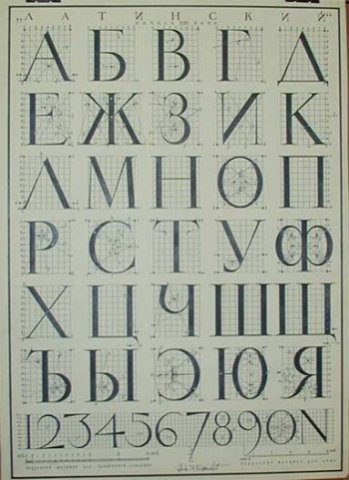
Антиквы
Их форма ведет свое происхождение от шрифта древнеримских монументальных надписей (прописные буквы) и от книжного гуманистического минускула эпохи Ренессанса (строчные буквы). Первая наборная антиква появилась в Италии и Германии во второй половине XV века. В дальнейшем форма латинской антиквы развивалась: на смену антикве старого стиля (конец XV – начало XVIII в.в.) пришла переходная антиква (начало XVIII – конец XVIII в.в.), которая сменилась антиквой нового стиля (конец XVIII – начало XIX в.в.), кроме того, в начале XIX в.появились брусковые шрифты. На основе этих исторических форм современные дизайнеры шрифтов создают новые версии антиквенных шрифтов.
Представляет собой первый этап развития антиквенных шрифтов (с конца XV по начало XVIII века). Форма знаков этого шрифта основана на дуктальном (рукописном) принципе, она характеризуется умеренной контрастностью, скруглением засечек в местах примыкания к основному штриху и наклоном осей овальных элементов.
Эти шрифты делятся на несколько подгрупп в соответствии с временем и местом своего появления: это венецианская антиква (конец XV века), итальянско-французская антиква (XVI век), голландская антиква (XVII век), английская антиква (начало XVIII века) и современные версии антиквы старого стиля.
Венецианская антиква
Ранняя антиква (конец XV века), включающая элементы готики. Этот шрифт иногда выделяют в отдельную группу классификации Humanist (так назывемая Гуманистическая антиква). Форма знаков основана на дуктальном принципе.
Шрифты характеризуются умеренной контрастностью, мощными короткими засечками, хорошо выраженным наклоном осей овалов и размашистыми пропорциями. Круглые элементы имеют каллиграфические изломы, капли угловатые. Среди исходных венецианских шрифтов этого периода нет курсивов, они были изобретены позднее.
Итальянско-французская антиква (Гаральды)
Представляет собой дальнейшее развитие венецианской антиквы в XVI веке. В этот период форма знаков французской антиквы все еще основывается на дуктальном принципе, однако она постепенно меняется под воздействием типографской практики и эстетических теорий того времени. Шрифты характеризуются небольшим контрастом, пропорциями золотого сечения, разноширинностью знаков, плавным присоединением засечек и наклонными осями овалов. Засечки становятся более длинными и острыми, а верхние выносные элементы, как правило, заметно выше прописных знаков. В этот период в качестве альтернативного текстового шрифта впервые применяется строчной курсив с небольшим наклоном.
Барочная антиква
Барочная антиква уже почти не напоминает гуманистический мину-
скул. Она заметно контрастнее венецианской и итало-французской, фор-
ма капель и других элементов в ней ближе к геометрически правильной,
кальная ось овала буквы о и наклонные — с и е.
Однако открытой формы знаков и общего характера набора достаточно,
чтобы барочная антиква оставалась динамической.
Разница в форме разновидностей барочной антиквы — голландской
и английской — невелика.
1. Голландская антиква
Представляет собой дальнейшее развитие форм французской антиквы в XVII веке.
Эти шрифты выполнены более качественно, для них характерно постепенное нарастание особенностей, свойственных глиптальным шрифтам (увеличение контраста и насыщенности, более острые засечки, оси овалов более вертикальны) при сохранении традиционной формы антиквы старого стиля. Шрифты довольно узкие, а очко строчных имеет более округлую форму. Рост прописных приближается к высоте верхних выносных элементов. В курсиве наклон у прописных меньше, чем у строчных. Строчные курсивные знаки имеют разный наклон. Угол наклона строчных знаков в курсиве больше, чем во французской антикве.
2. Английская антиква
Шрифты первой половины XVIII века, созданные в Англии как улучшение голландской антиквы. Детали почти целиком определяются глиптальными принципами, однако форма знаков в значительной степени традиционно повторяет более раннюю антикву старого стиля. Знаки этих шрифтов более контрастны и насыщены, засечки тоньше и острее, а оси овалов почти вертикальны. Пропорции знаков гораздо шире, чем в голландской антикве, знаки разноширинные.
Современные версии шрифтов на основе антиквы старого стиля, не имеющие конкретных прототипов и отличающиеся по форме.
Переходная
Шрифты начала и середины XVIII века, сочетающие черты шрифтов старого стиля, характерные для письма широким пером, и элементы шрифтов нового стиля, форма которых связана с особенностями процесса гравировки по металлу.
Эта форма переходной антиквы почти не связана с антиквой старого стиля. Она основана на глиптальных принципах, связанных с рисованием и гравировкой металлических пуансонов. Знаки более контрастны, а соединительные штрихи и засечки тоньше, чем в антикве старого стиля. Скругления засечек в местах соединения с основными штрихами выражены слабо. Оси овалов некоторых знаков почти вертикальны, у остальных знаков они имеют незначительный наклон.
Современные вариации шрифтов на основе переходной антиквы, не имеющие конкретных прототипов и отличающиеся по форме.
Нового стиля
Эти шрифты появились в конце XVIII – начале XIX века в связи с развитием техники гравировки по металлу. Одноширинные шрифты с сильным контрастом. Засечки длинные и тонкие, оси овалов строго вертикальны. По форме засечек антиква нового стиля делится на следующие группы: классицистическую, англо-шотландскую и современные вариации шрифтов на основе антиквы нового стиля.
Классицистическая антиква
Антиква Жоффруа ТориВ XVIII в.
под влиянием стиля классицизма и техники оригинальной гравюры на меди антиква меняет свои формы — возникает новая антиква, отличающаяся от старой утонченностью форм и очень большим контрастом. В буквах этого шрифта доминирует вертикаль, наблюдается сужение пропорций и глубина пространства. Соединительные штрихи стали очень тонкими, а засечки длинными. Буквы освободились от тяжелых закруглений, которые в старой антикве соединяли засечки с основными штрихами. Шрифт стал легким и изящным.